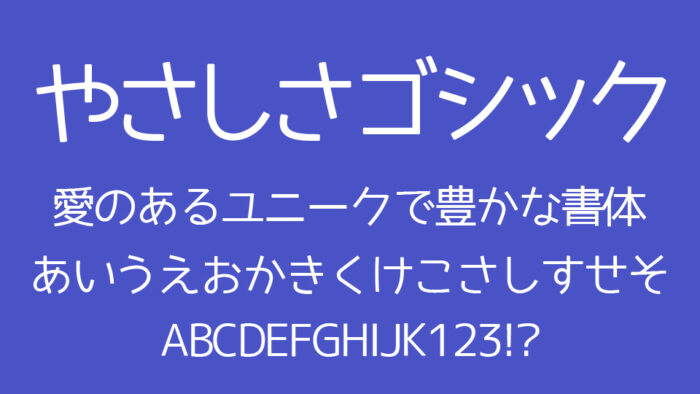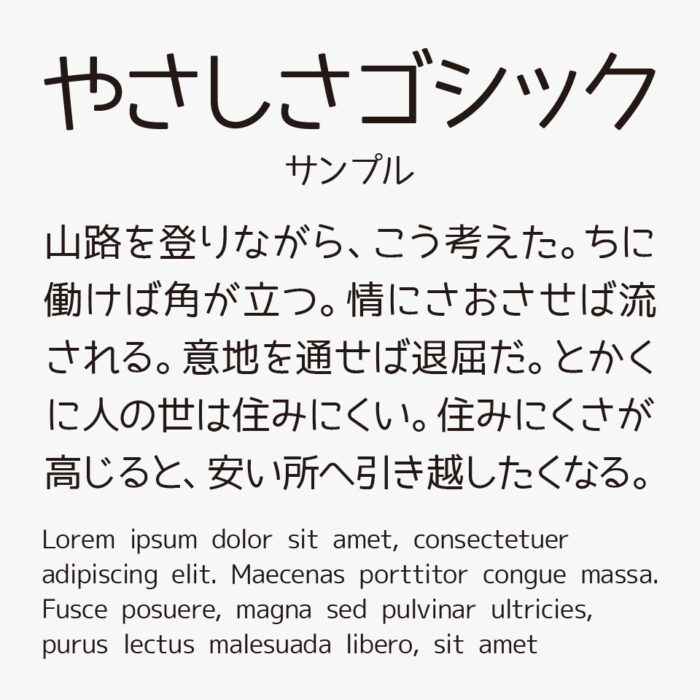
やさしさゴシック
やさしさゴシックフォントは、作者さまが「優しい気持ち」で作成した柔らかく優しい印象があるゴシック体フォントです。
ベースはゴシック体ですが、全体的に丸みや手書き風のようなデザインとなっているので、親しみ感や優しさを感じられるフォントです。
漢字も豊富に揃っており、文字の可読性も非常に優れているので、デザインシーンだけではなく、資料作成やプレゼンなど幅広いビジネスシーンで活躍できるフォントです。
収録文字は、数字、アルファベット、記号、かな文字(ひらがな・カタカナ)、教育漢字、常用漢字、第一水準漢字、第二水準漢字、その他主要な多言語が収録されています。